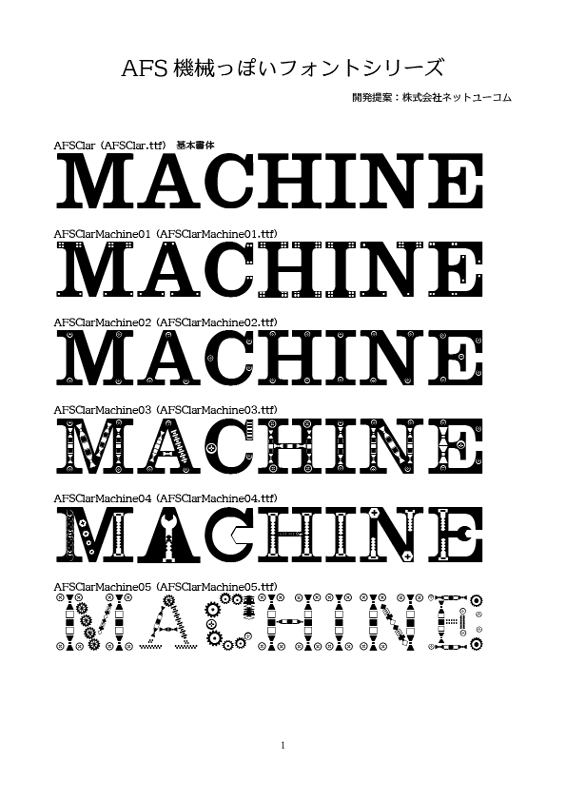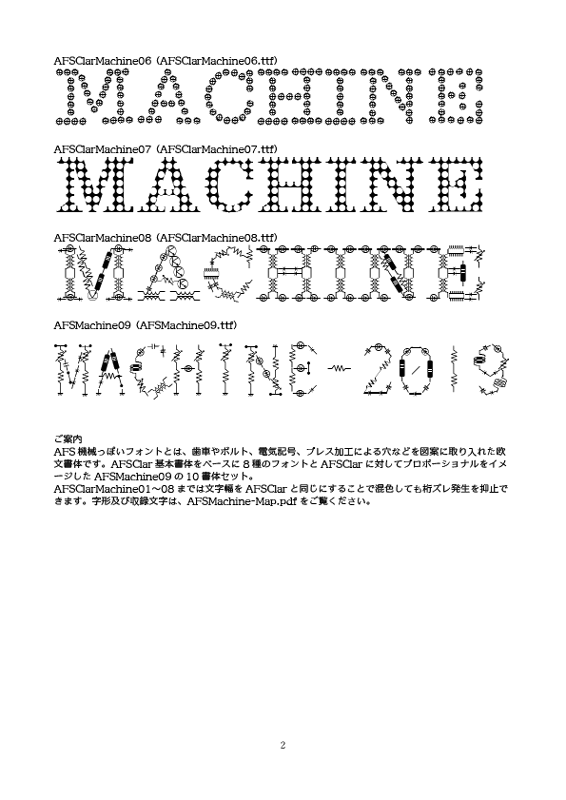
AFS 機械っぽいフォントは、歯車やボルト、電気記号、プレス加工による穴などを図案に取り入れた欧文書体。AFSClar 基本書体をベースに8 種のフォントとAFSClar に対してプロポーショナルをイメージしたAFSMachine09 の10 書体セット。AFSClarMachine01~08 までは文字幅をAFSClar と同じに
することで混色しても桁ズレ発生を抑止できます。字形及び収録文字は、AFSMachine-Map.pdf をご覧ください。